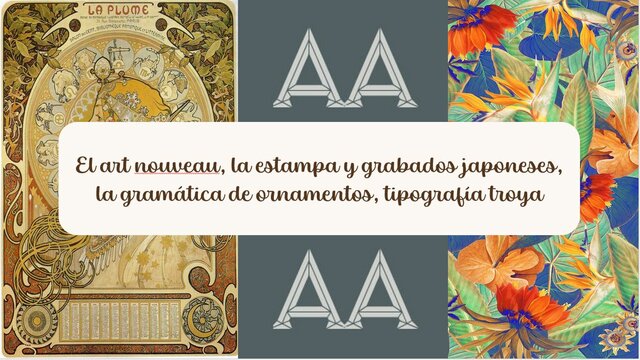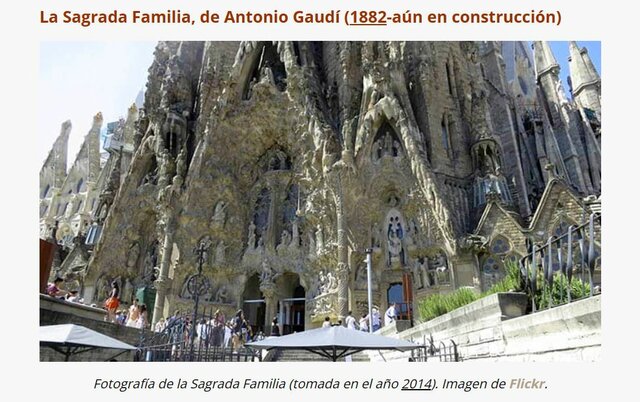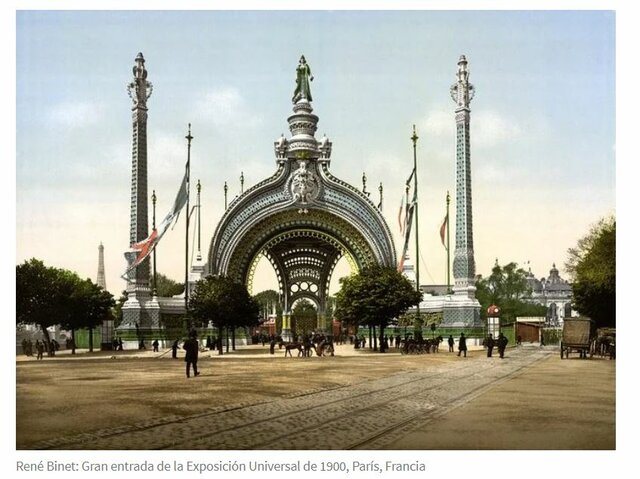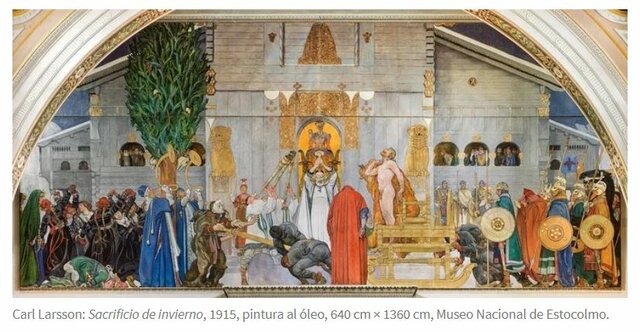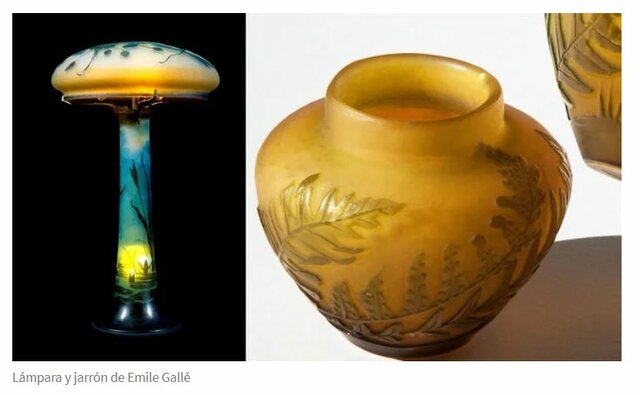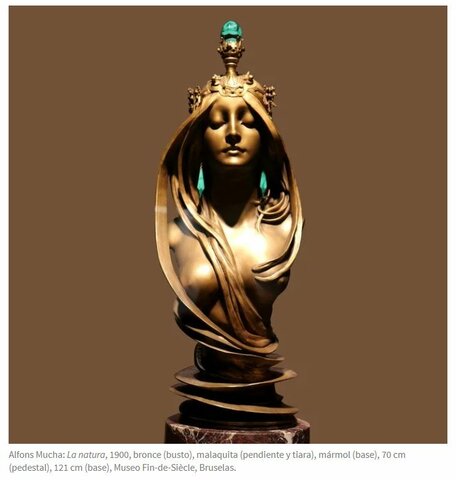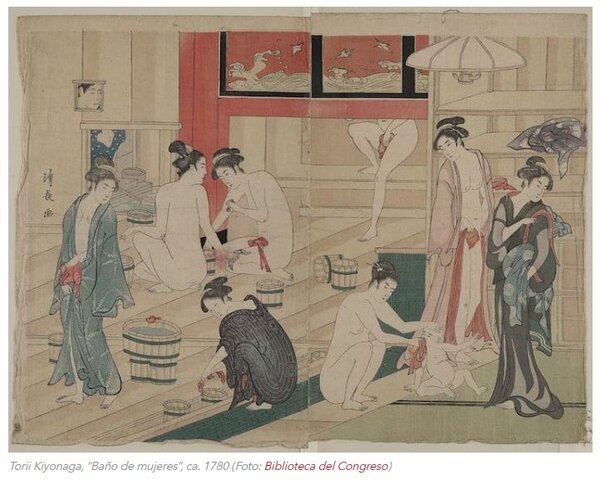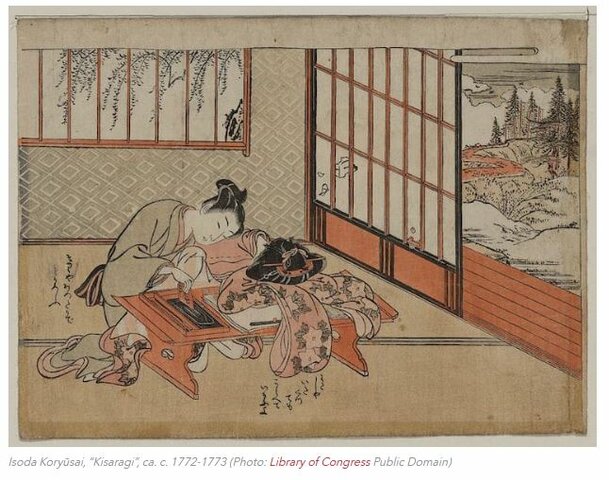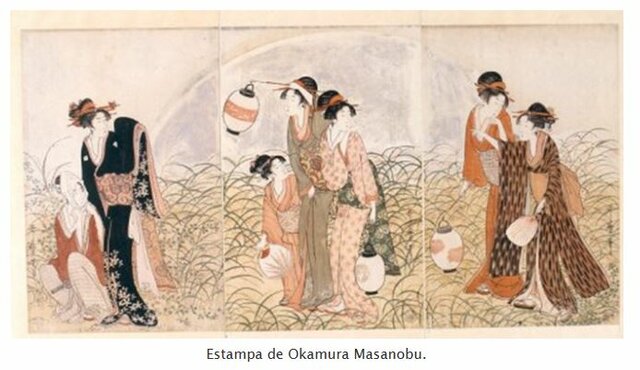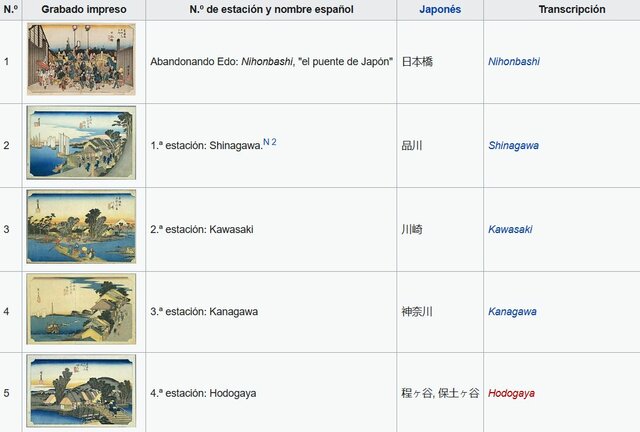
El art nouveau, la estampa y grabados japoneses, la gramática de ornamentos, tipografía troya
Introducida durante la dinastía Han de China, que duró desde el 206 a.C. C. hasta el 220 d. C., el arte de la imprenta se popularizó en Japón hasta el período Edo, una era que se extiende desde 1603 hasta 1868. El proceso se utilizó inicialmente para reproducir rollos. Sin embargo, fue adaptado y adoptado como un medio para producir impresiones en masa.
Alcanzando su popularidad en la cultura Edo metropolitana durante la segunda mitad del siglo XVII, esta forma de arte se originó con las obras de un solo color de Hishikawa Moronobus en la década de 1670. Utilizaba tinta china y posteriormente se coloreaban a mano algunas estampas con pinceles. -
El desarrollo de la técnica de impresión en color fue fuertemente promovido por Suzuki Hanobu, quien alrededor de 1765 pasó de la ilustración de libros al diseño de impresiones individuales. Usó un método de impresión con al menos cinco colores, además de usar sobreimpresión y estampado. -
INTERIORES
Otro tema que atrajo a los artistas de ukiyo-e fueron las escenas interiores sencillas. Combinando líneas limpias de la arquitectura japonesa y el estudio y la representación de la vida silvestre cotidiana, estas representaciones a menudo aparecían en el interior de sus hogares desde un punto de vista voyeurista. bañar, cuidar niños y tomar té son algunas de las tareas realizadas por las figuras representadas. -
COMPOSICIONES PLANAS
Si bien la mayoría de los artistas que giran sobre el papel tienen como objetivo adquirir sentidos realistas de la perspectiva, aquellos que se especializaron en grabados en madera se preocuparon poco por la profundidad y las dimensiones. Prefirieron las formas fuertes, los diseños gráficos y las líneas nítidas. Los artistas prefieren toques de color, hermosos temas e incluso composición para lograr una perspectiva precisa. -
MUJERES
La mujer de belleza clásica es un tema recurrente en las obras japonesas. Las mujeres japonesas, desde geishas y cortesanas hasta jóvenes comunes, parecen haber fascinado a los artistas de los grabados en madera. Estas representaciones de mujeres se conocían como Utamaro. Acertadamente llamado bijin ōkubi-e ("imágenes de mujeres hermosas con cabezas grandes"), sus retratos presentaban vistas de los rostros y la parte superior del cuerpo de las mujeres, enfatizando su belleza natural. -
Hiroshige mostró los efectos dramáticos y poéticos de los fenómenos naturales. Fue uno de los últimos representantes del grabado ukiyo-e, que llevó a un nivel de alta calidad antes del declive de la impresión xilográfica en Japón. Fue un humilde intérprete de la naturaleza, pero sobre todo se mostró como un verdadero genio cuando se valió de los limitados medios del grabado sobre madera para expresarse, haciendo emerger de la atmósfera delicadas transparencias al compás de las estaciones. -
Owen Jones dice que una forma sin color es como un cuerpo sin alma y que el color es tan importante como los diseños.
En 1844, Aunque elogiado, su diseño para los pisos del Palacio de Westminster no fue aceptado. -
La aparición, hacia 1850, del oro y la plata refleja más tarde el nuevo gusto por la opulencia. Los artistas japoneses utilizaron líneas curvas y planos de color para crear imágenes eróticas de belleza femenina. El teatro kabuki ofreció una rica estética materialista para la inspiración, así como modelos con sensibilidad y poesía, y que expresaron la atracción japonesa por las funciones. -
Llamó la atención sobre la belleza de su taller y los métodos utilizados para predecir sus diseños, que se basan en modelos en lugar de planos. Estaba interesado en aprender sobre el gótico y otros estilos históricos. Quería usarlo para expandir las posibilidades del nuevo arte. Entre sus obras más famosas se encuentran el Templo Expiatorio de la Sagrada Familia, el Parque Güel y la Casa Batló.
Escrito por Jones y publicado por primera vez en 1856, convirtiéndose en un referente para el aprendizaje de los diseñadores de artes decorativas de su época. Owen Jones había viajado por distintos países absorbiendo la cultura de cada uno de ellos y plasmando así diferentes estilos ilustrativos y ornamentales como el árabe, persa, italiano, chino e hindú entre otros. -
Con la ayuda de Henry Cole, Jones desarrolló sus principios de decoración en 37 axiomas de diseño, que aparecen en su influyente publicación The Grammar of Ornament en 1856. Trabajó en casi todas las ramas de la decoración, sedas, diseño de empaques comerciales, edificios públicos y mansiones privadas durante su vida. -
UNA RICA PALETA DE COLORES Aunque la producción de los grabados fue un proceso rápido y aparentemente mecánico, sus ricos tonos recuerdan a las pinturas meticulosamente coloreadas a mano. Los grabados en madera más famosos están dominados por rojos, azules y verdes e incluso negros profundos. -
NATURALEZA
La pintura Art Nouveau también se conoce como pintura modernista. Dominando el simbolismo de Jean Moréas, enfatiza lo imaginario, lo onírico, lo ajeno y lo artificial, rechazando los temas históricos o cotidianos del arte académico.
Los pintores del Art Nouveau no compartían un estilo unificado, pero sí ciertas características como:
-Contornos pronunciados;
-Líneas ondulantes y entrelazadas;
-Motivos vegetales;
-Decorativismo.